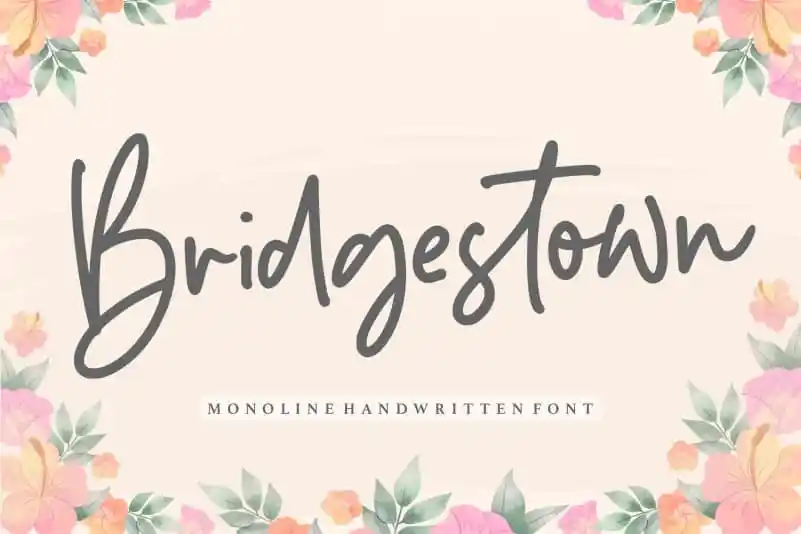
Bridgestown Monoline Handwritten Font – Download Grátis
A fonte ‘Bridgestown Monoline Handwritten Font’ é ideal para quem busca uma elegância sofisticada com um toque delicado de escrita à mão. Confeccionada por Balpirick, essa fonte é perfeitamente adaptável a diversos usos, desde embalagens de produtos até projetos de marca e revistas digitais, sem esquecer das mídias sociais e dos eventos como casamentos. Suas linhas simples e acentos finos criam um contraste que destaca qualquer texto sobre o qual seja aplicado, tornando-a perfeita para expressar ideias em alta projeção. Seja para destacar uma marca, dar identidade a uma linha editorial ou apenas criar um impacto visual forte em sua próxima peça de design, ‘Bridgestown Monoline Handwritten Font’ está certa para o seu projeto.